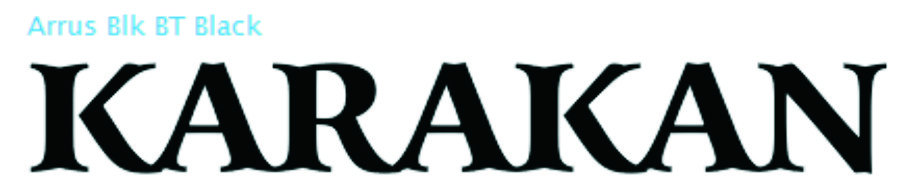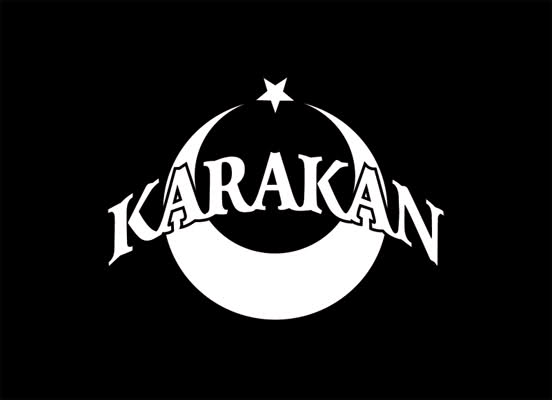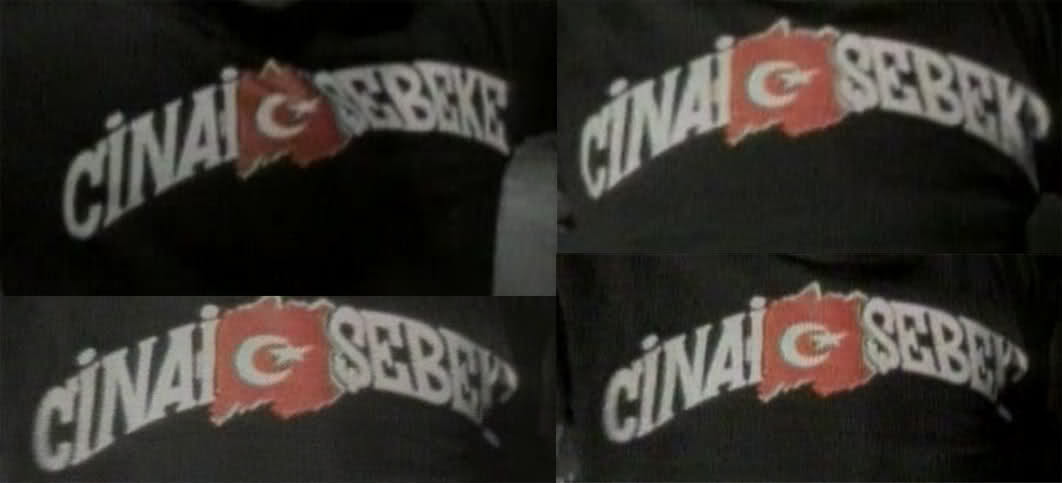
Wie heisst dieser Schrift und welcher Schriftart ist das?
bin schon seid langer Zeit verzweifelt auf der Suche nach dieser Schriftart, die Ihr auf dem Logo sehen könnt.
Wie heisst dieser Schrift genau bzw. der Font?
Hallo, das ist die Arrus Bold.
Leider habe ich da noch was, was ich auch wieder nicht raus finden kann.
Es geht um diesen Schrift, die du in den einzelnen Bildern sehen kannst.
(Siehe Bild --->)
Hab auch wieder überall durchsucht, wieder nicht raus bekommen um welchen Schrift es sich handelt. Bitte zum letzten mal nochmals um Hilfe.
Das ist sehr schwer, versuche es mal mit der Boton Bold.
Habe das mit der Boton Bold + Boton Pro versucht aber vergeblich.
Es hat schon in einigen ecken und kanten ähnlichkeit aber ist nicht leider nicht das was ich suche.
Kann es sein dass dieser Schrift vielleicht selbsterfunden bzw. bearbeitet wurden ist?
Ich würde das gerne wie das Logo von "Karakan" vorzeigen aber leider existiert die 2. Logo was ich vom Video entnommen habe nicht. Soweit ich mich informiert habe wurde das Logo Extra nur für das Videoclip erstellt und ausser das Video sieht man nirgendswo die 2. Logo.